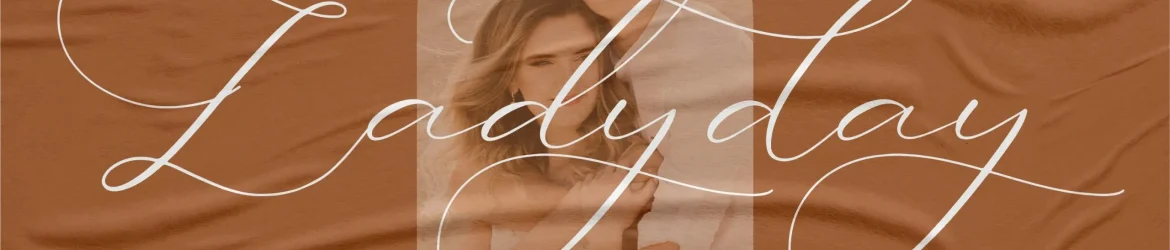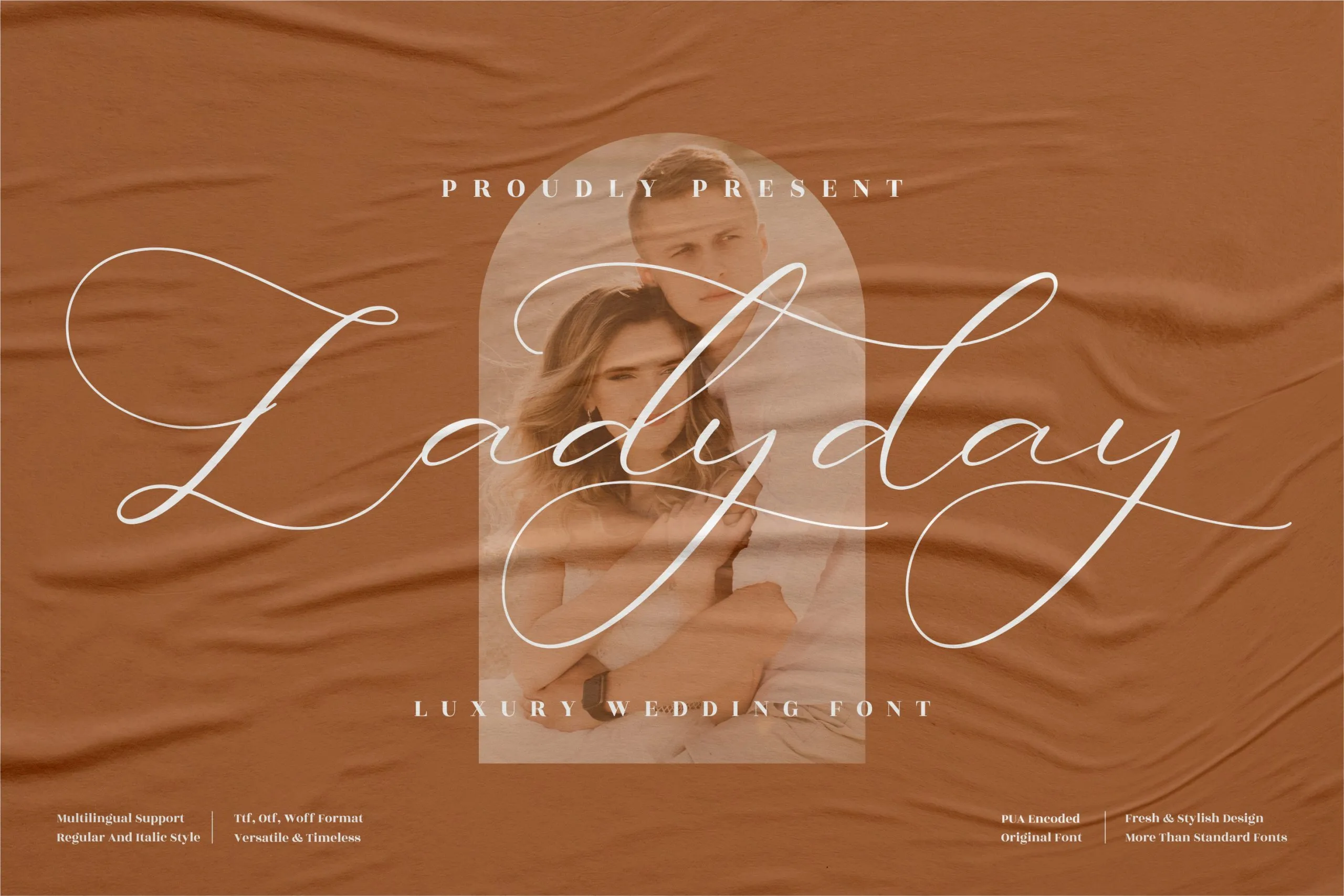
Ladyday Font – Fonte Grátis
Ladyday Font
Esta é uma fonte de escrita romântica perfeita para projetos variados, desde logomarcas até cartões de agradecimento e embalagens personalizadas. A Ladyday Font foi criada com designer perspectype para trazer beleza única e singular a qualquer projeto que precise de um toque delicado e charmoso. Seja você uma marca em busca de um visual único, um designer especializado em design gráfico ou alguém apaixonado por fazer arte personalizada, essa fonte é o seu companheiro ideal. Aplicada em logos e camisetas, nome cards e embalagens, a Ladyday Font adiciona aquele toque que faz toda a diferença. Que tal dar vida ao seu próximo projeto com uma pitada de romantismo? Download hoje e veja como essa fonte se transformará em sua obra-prima!